我们经常会问,英文可商用字体哪里下载?不用担心,素材君整理了2020年3月特别受欢迎可商用英文字体合集,推荐收藏。
一款讲究易读性的无衬线字体,为设计营造出魅力十足的氛围。
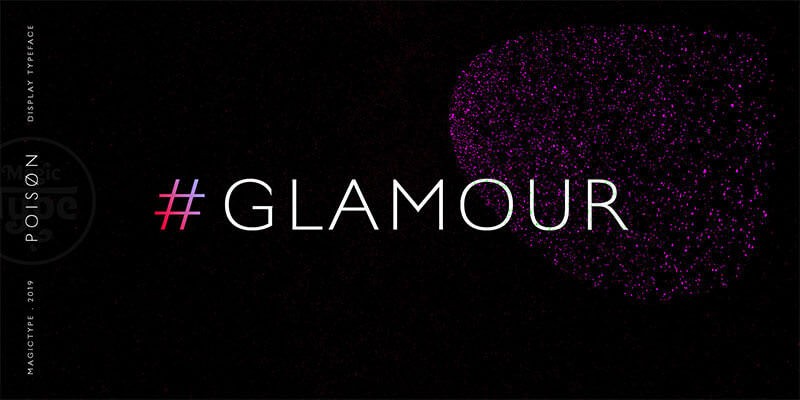
从超细的发线字体到粗体字共5种万能字体的字型。
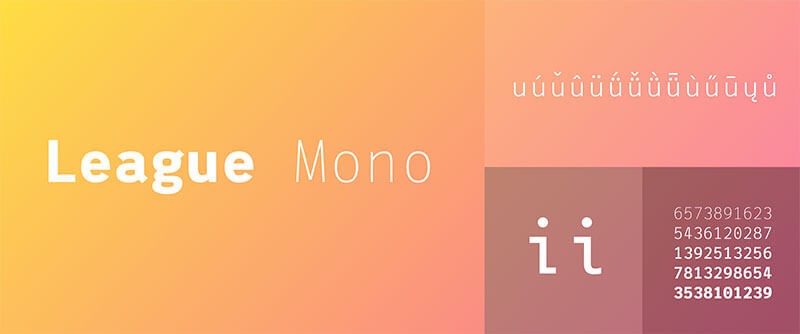
超经典字体Copper Black,2020年更新字体。更时髦复古。
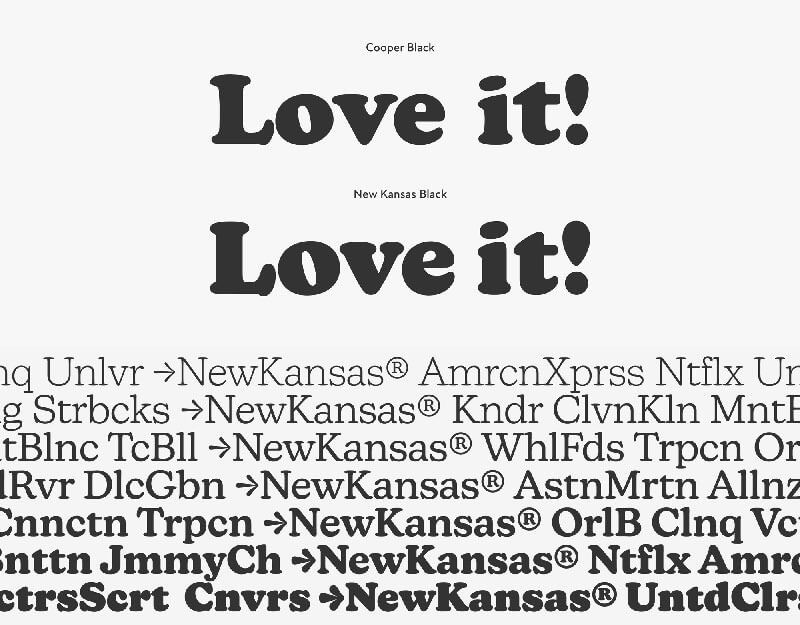
给人一种时空错乱的字体,很有个性。
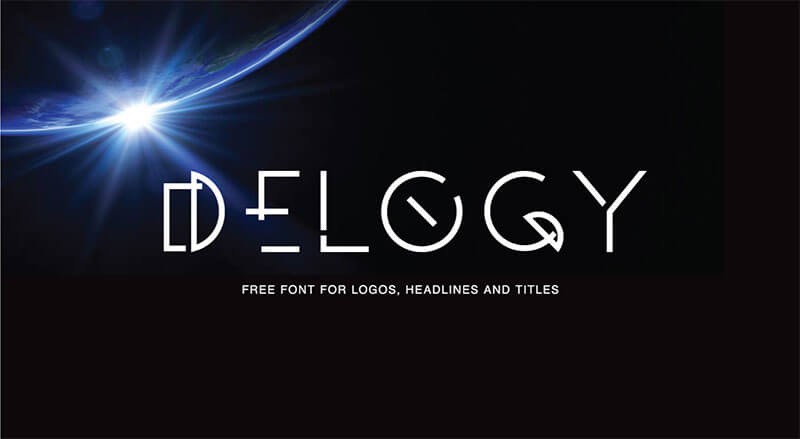
一种休闲签名风格的免费字体,自然手绘风格,可以直接作为书面写作使用。
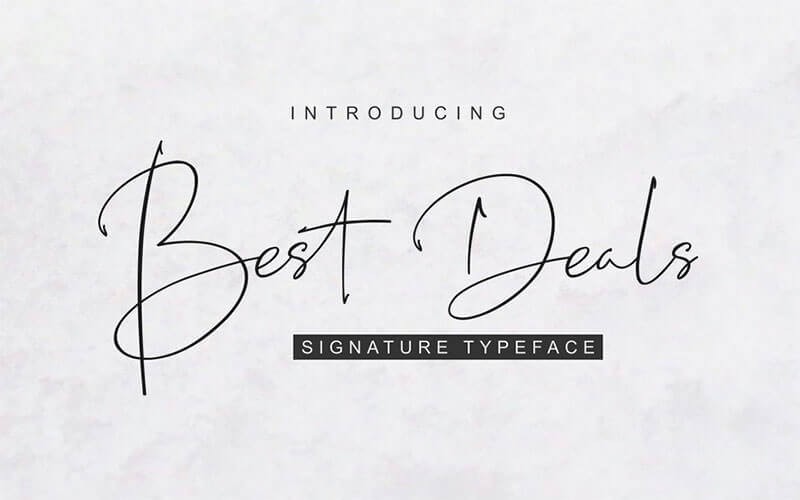
手绘笔刷字体,可广泛使用品牌、徽标制作、婚礼邀请函等。
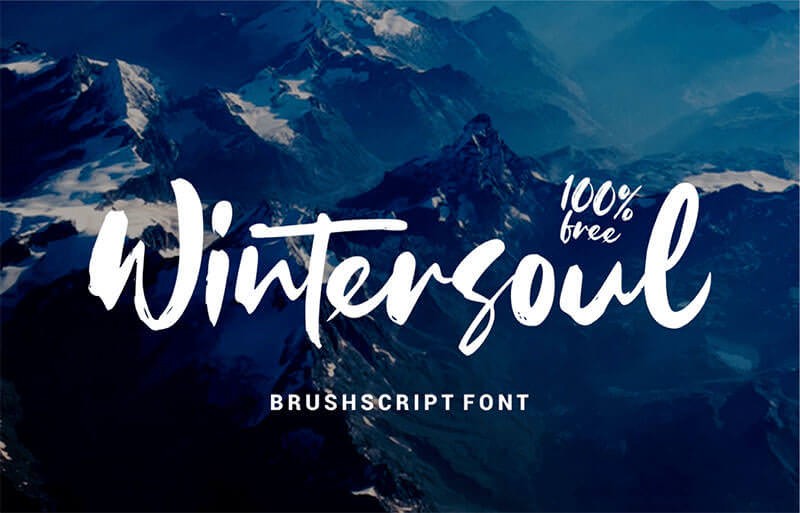
收录超过130个字形字符,2种风格的开源免费字体。
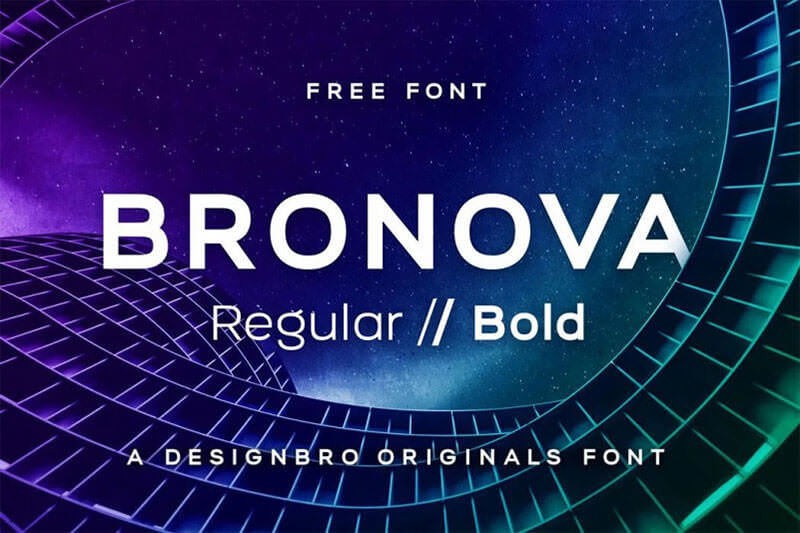
清晰的棱角风格的字体。
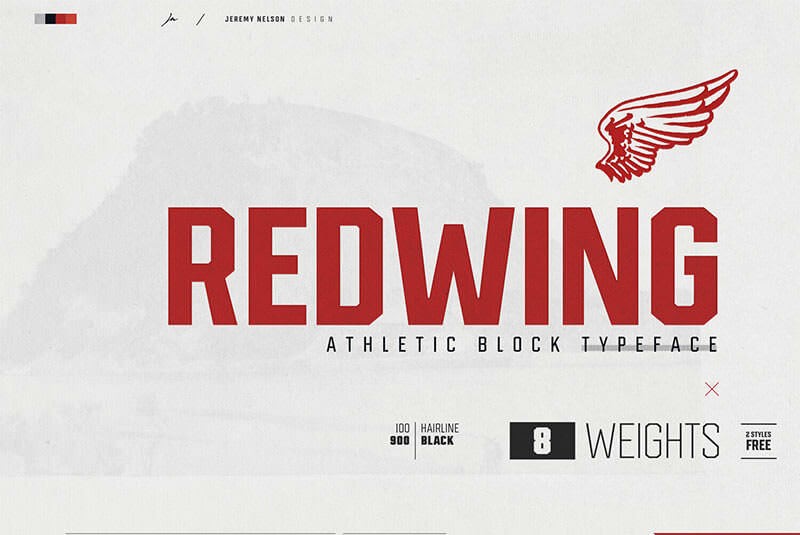
精美的英文字体,注重简单性、可读性和功能性。光滑的曲线曲线是令人印象深刻的风格,非常适合复古的氛围。
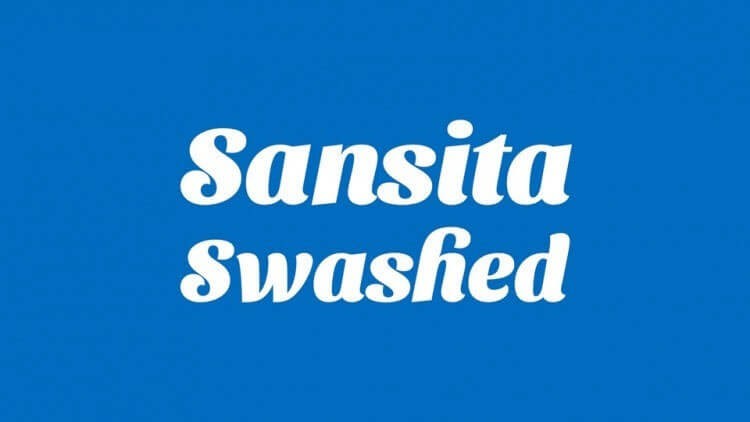
个性缺失免费英文字体。
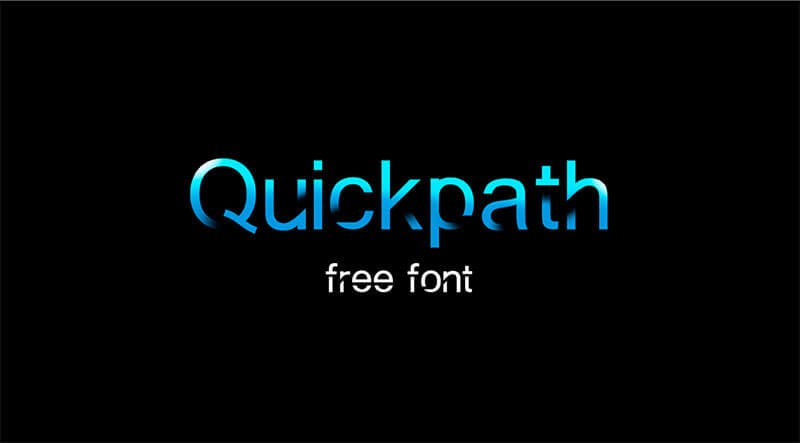
这是一种时尚的舞台英文字体,非常适合短单词和消息的显示。
除了字母以外,还对应数字和特殊符号,丰富的密语合字一应俱全的签名免费字体。
像是乱写的手写签名免费字体,除了数字和符号,还支持密语合字。
自然手写笔刷风格免费字体。婚礼邀请函、T恤标识、贺卡等广泛使用的项目。
手写连笔英文字体,很适合用在婚礼、邀请函和品牌设计的签名免费字体。
一款厚重的手写素描字体。
手写粗糙的粗体字免费字体。
独特的字母字体,以西藏和尼泊尔语为主题创建。
营造圆润欢乐氛围的字体风格。
独特的免费字体,让人联想到糖果。